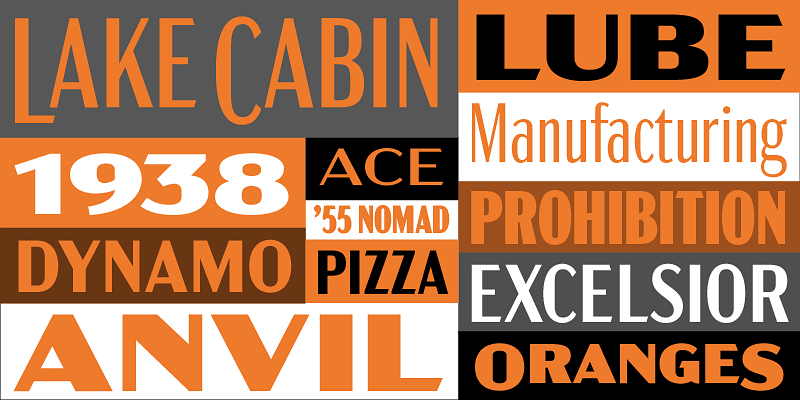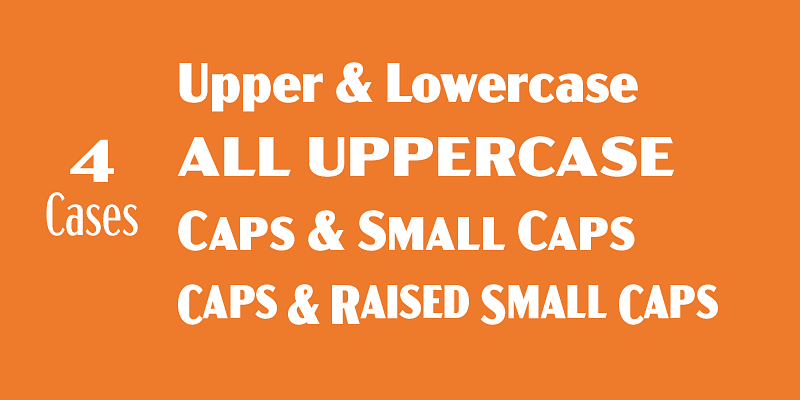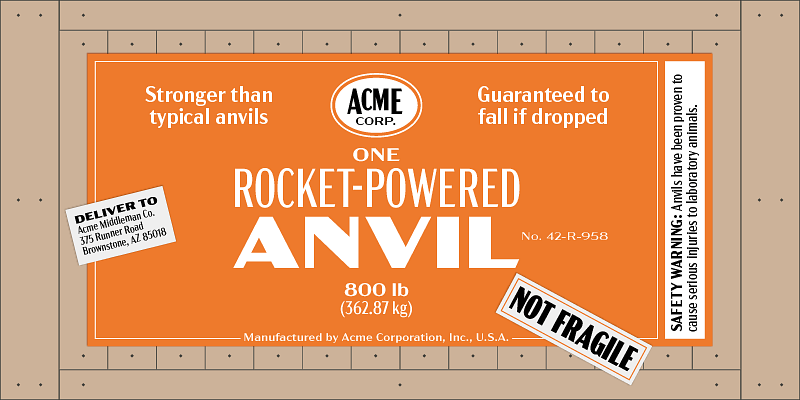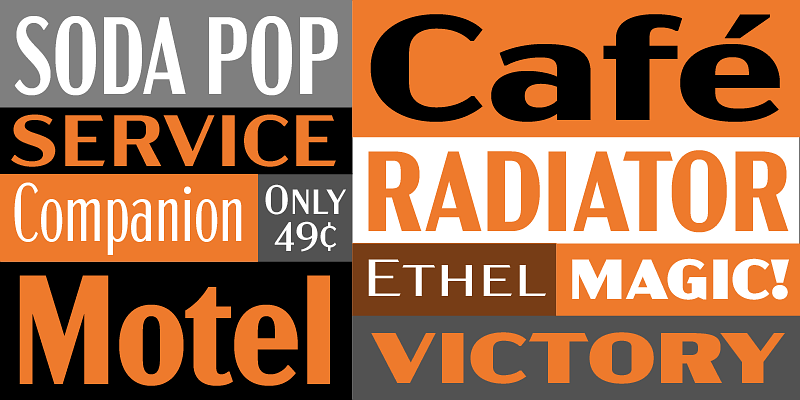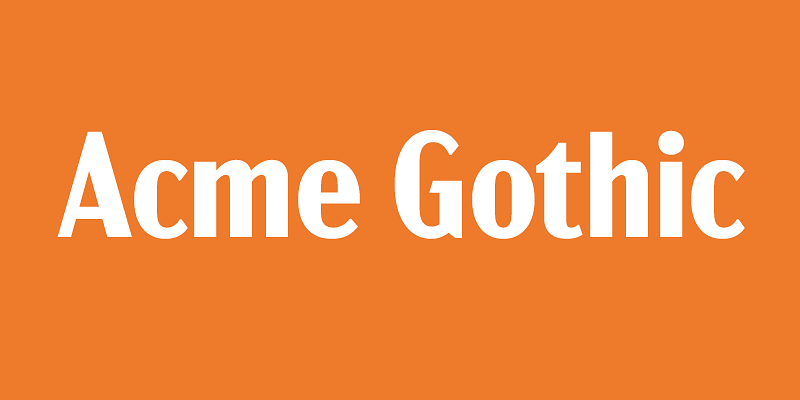
Acme Gothic (2018) s’inspire du style gothique, typographiquement épais et fin, populaire aux États-Unis dans la première moitié du XXe siècle. Des polices de ce genre ont déjà existé, mais elles étaient soit trop originales (Globe Gothic), trop anglaises (Britannic), trop Art déco (Koloss), trop modernes (Radiant) ou trop Art nouveau (Panache). Aucune ne parvient à restituer le style simple, artisanal et vernaculaire d’Acme Gothic. Cinq largeurs (Compressed, Condensed, Normal, Wide et Extrawide), disposant chacune de cinq épaisseurs (Light, Regular, Semibold, Bold et Black), totalisent 25 styles différents.